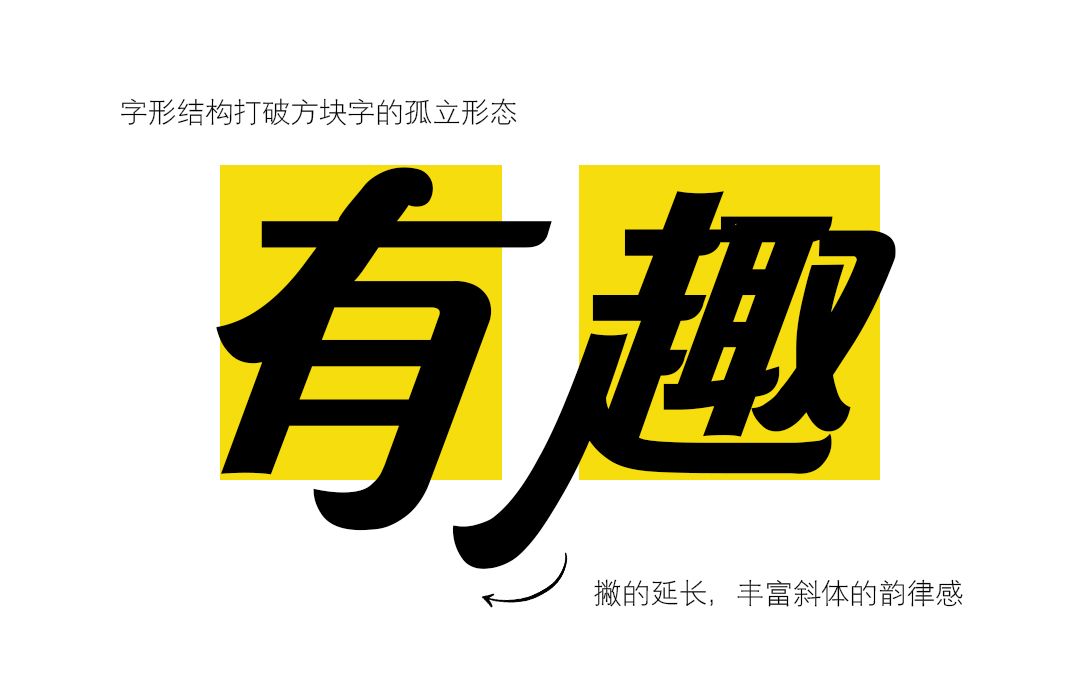
优雅又高级的中文字体——造字侠郝刚快乐简
一搜优雅、高级感的字体相关关键词都是英文字体,纤细的字符、优雅的弧线确实别有一番风情。在中文字体中,有一款兼具西文优雅斜体韵律又融合中式隶书的美感字体——造字侠郝刚快乐简。
造字侠郝刚快乐简采用中西结合的设计手法,一方面糅合西文斜体装饰风格的浪漫优雅,字体倾斜112度;一方面运用汉字隶书笔画的撇、捺错落变化,在蚕头燕尾的韵味中,构建斜体字的韵律感、节奏感;在微妙的平衡感中,创造轻松明快的自洽节奏,也是对字体美感的均衡把控。